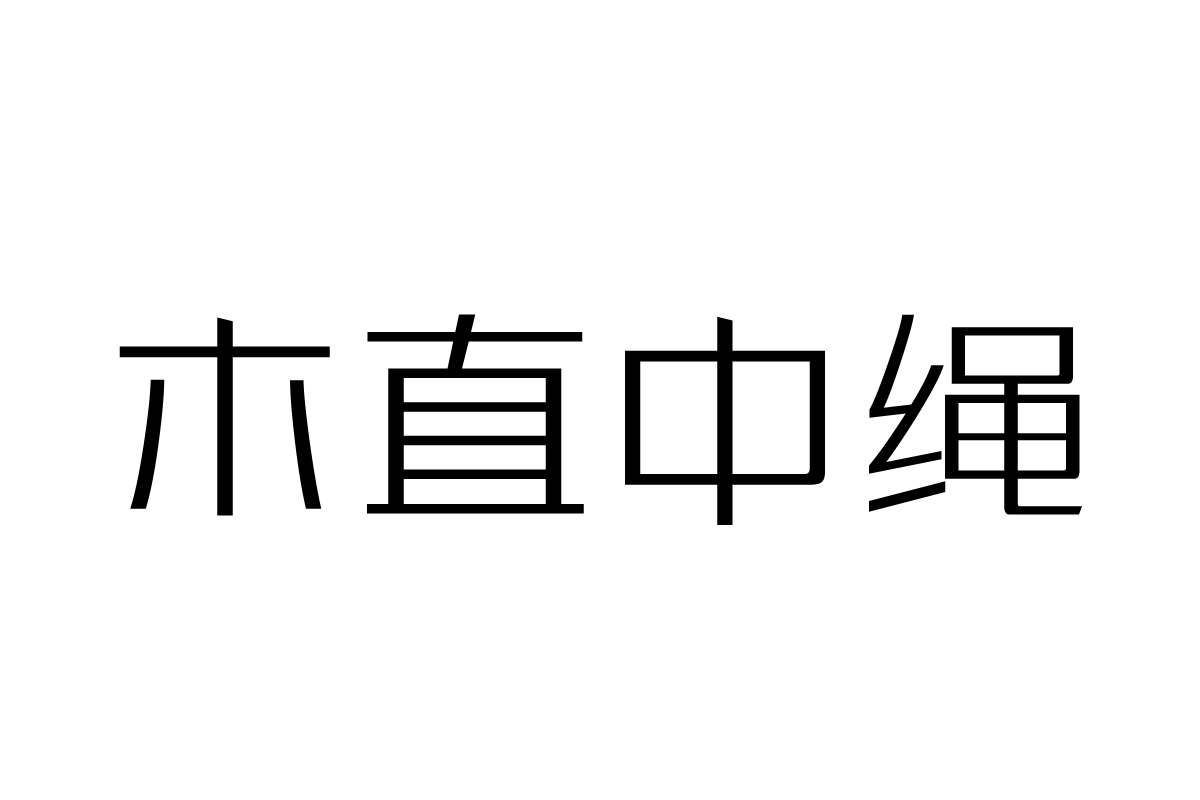
“三极力量酷黑 极细”是一种字体,由”三极力量”和”酷黑”以及”极细”三个词汇组成。这种字体可能具有以下特点:
1. “三极力量”:这个词汇可能表示这款字体的力量感,给人一种强大、有力的感觉。
2. “酷黑”:这个词汇可能表示这款字体的颜色为黑色,给人一种神秘、酷炫的感觉。
3. “极细”:这个词汇可能表示这款字体的字号非常小,适合用于需要强调细节或者需要缩小字体的场合。
总的来说,”三极力量酷黑 极细”这种字体可能是一种具有强烈视觉效果的字体,适合用于需要强调力量、酷炫或者需要缩小字体的场合。